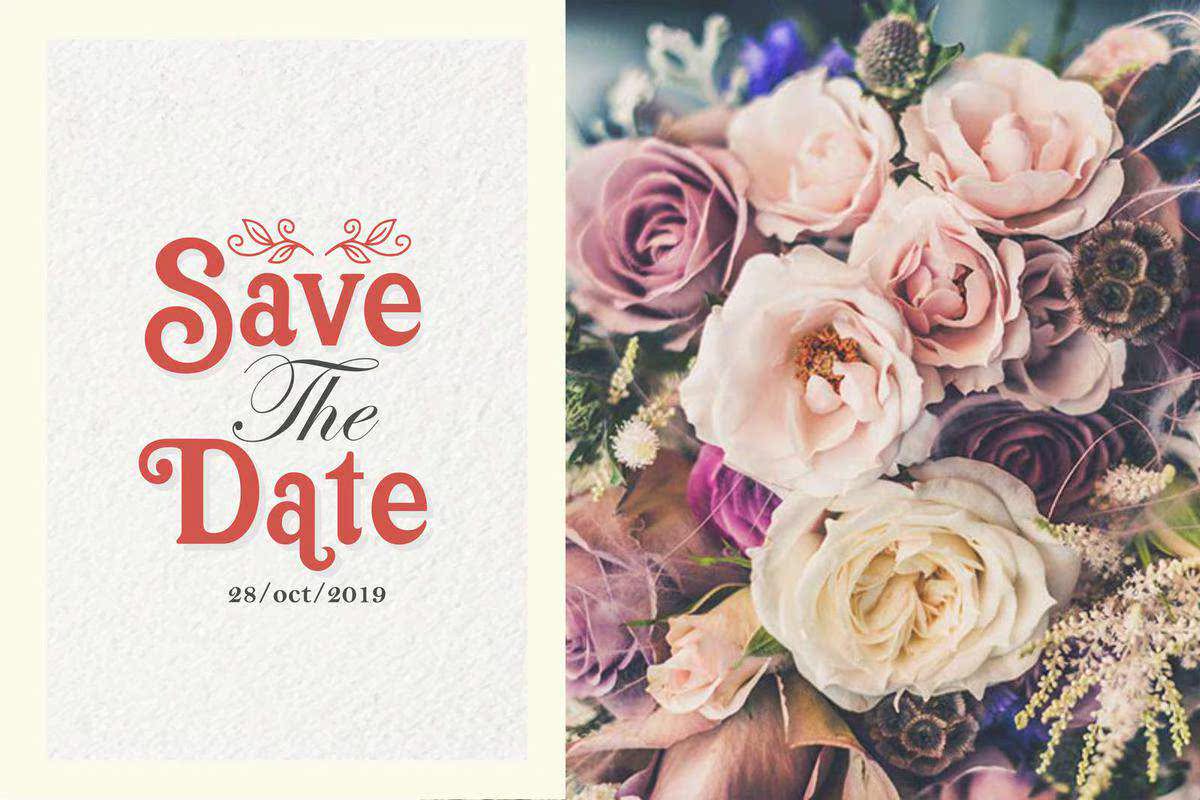
HOLIDAYFont–介绍–HOLIDAYFont!新字体具有一组较大的双向可选字符。HolidayFont是一种现代化的字体,每个字母都有漂亮的字体。它包含一组较大的初始字符和一组较大的字符,具有更多的可选字符!!HOLIDAYFont允许您在短短几分钟内阅读头条、徽标和美景。HOLIDAYFont–介绍–HOLIDAYFont!新字体具有一组较大的双向可选字符。HolidayFont是一种现代化的字体,每个字母都有漂亮的字体。它包含一组较大的初始字符和一组较大的字符,具有更多的可选字符!!HolidayFont允许您在短短几分钟内浏览头条新闻、登录和美容。